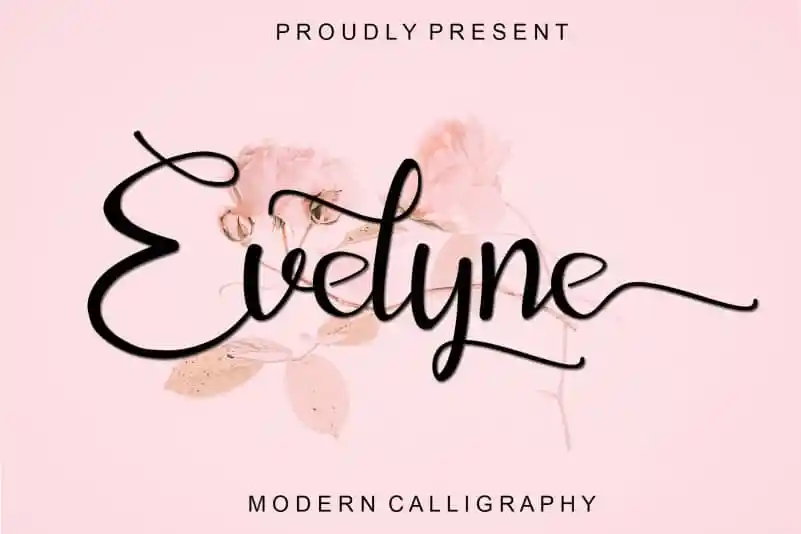
Evelyne Calligraphy Font – Download Grátis
A Evelyne Calligraphy Font é uma elegante tipografia manuscrita que transmite sofisticação através dos traços finos e delicados. Desenhada meticulosamente para se tornar um verdadeiro favorito, mantém os influentes traços da calligrafia enquanto aparenta ser contemporânea e atual. Esta fonte traz uma sensação feminina, enriquecendo designs de maneira suave e sofisticada. Perfeita para invitations de casamento, citações, marcação e embalagens, entre outros usos criativos, a Evelyne atende aos mais exigentes desejos de design.